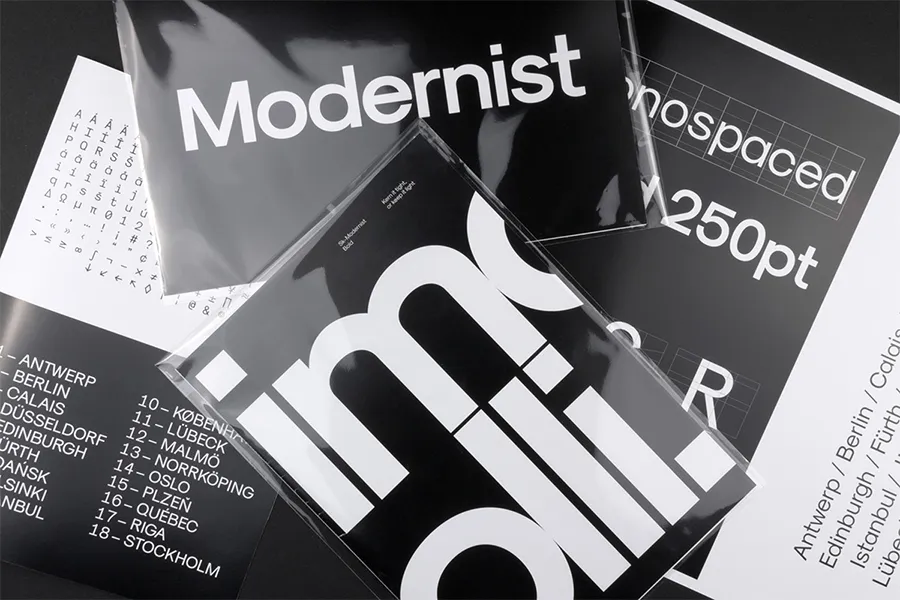
Modernist é uma fonte sans-serif que combina elementos de formas simplificadas e modernas. Inspirada na estética pura do Helvetica e na simplicidade geométrica do Avant Garde, essa fonte foi projetada para atender às necessidades da era digital. Cada forma de letra foi ajustada opticamente usando uma sistema matemático, em vez dos olhos tradicionais dos tipógrafos. Esta opção tecnológica não apenas garante uma leitura legível e precisa em qualquer tamanho ou dispositivo, mas também mantém a simplicidade essencial que torna essa fonte tão popular no design digital atual. Seja para aplicativos de trabalho, materiais educacionais ou criações artísticas digitais, Modernist é uma opção perfeita para quem busca elegância e eficiência em um único desenho.